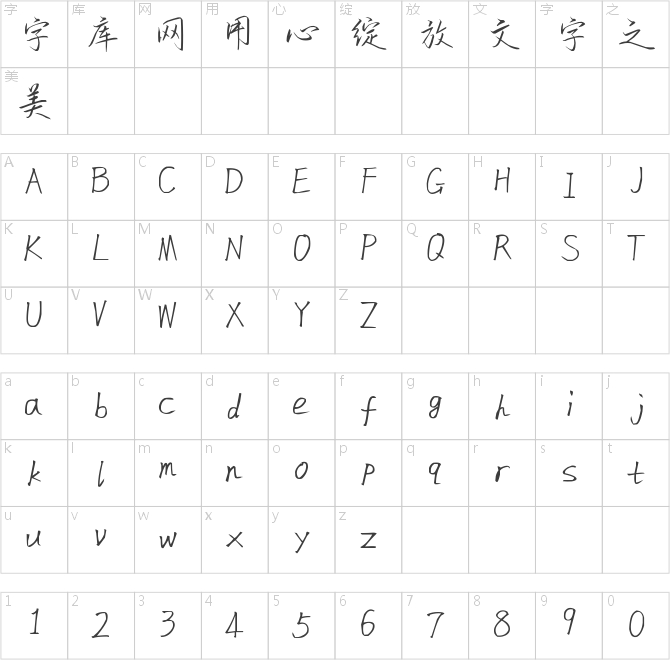
字體名稱: 能哭能笑能盡歡
起筆手筆行如流水,從容不迫,結構嚴謹不呆板,起收筆間體現良好的書法功底,連筆較多也不影響閱讀。整體閱讀起來,字體的跳動非常的愉悅舒適。
能哭能笑能盡歡字體字庫是一款讓人賞心悅目、百看不厭的中文字體,適合各類廣告和產品包裝設計應用,字體大小3.3MB,格式為TTF字體,上傳用戶是g05662,作者/版權方為方正手跡